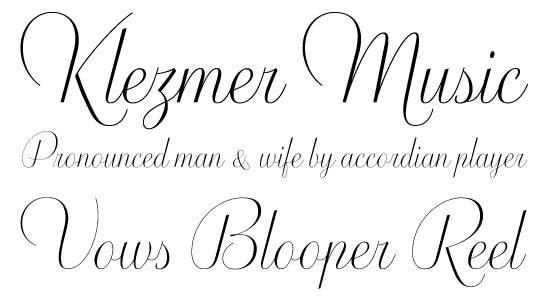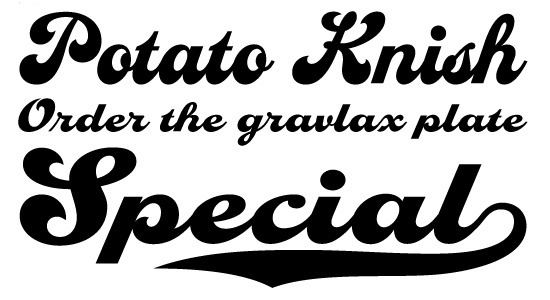
Biscotti & Casey (Font Bureau)
zwei neue schriften bei font bureau ...
Biscotti was commissioned in 2004 by Gretchen Smelter and
Donna Adjerian for Brides magazine. Cyrus Highsmith has prepared
a radically simple descendant of the flourished engraved scripts
traditionally deemed suitable for such formal occasions, a 21st century
typeface that captures the smiling spirit of these classical forms.
Casey, Leslie Cabarga’s latest script, recalls Casey at the Bat,
Ernest Lawrence Thayer’s vivid old baseball poem. Once, fat-bottomed
scripts like Casey were everywhere. Today they often survive as
logos for Campbell’s soup, Ford, Coca Cola, and, of course, the Dodgers,
yet no recent baseball jersey has been complete without lettering
embroidered in this classic form.
wollte gerade schreiben das die casey ähnlich wie eine schrift von
leslie cabarga aussieht. :oops: ähm, naja dann war es wohl doch
die gleiche, die habe ich vor zwei wochen auch entdeckt und für
hübsch befunden.